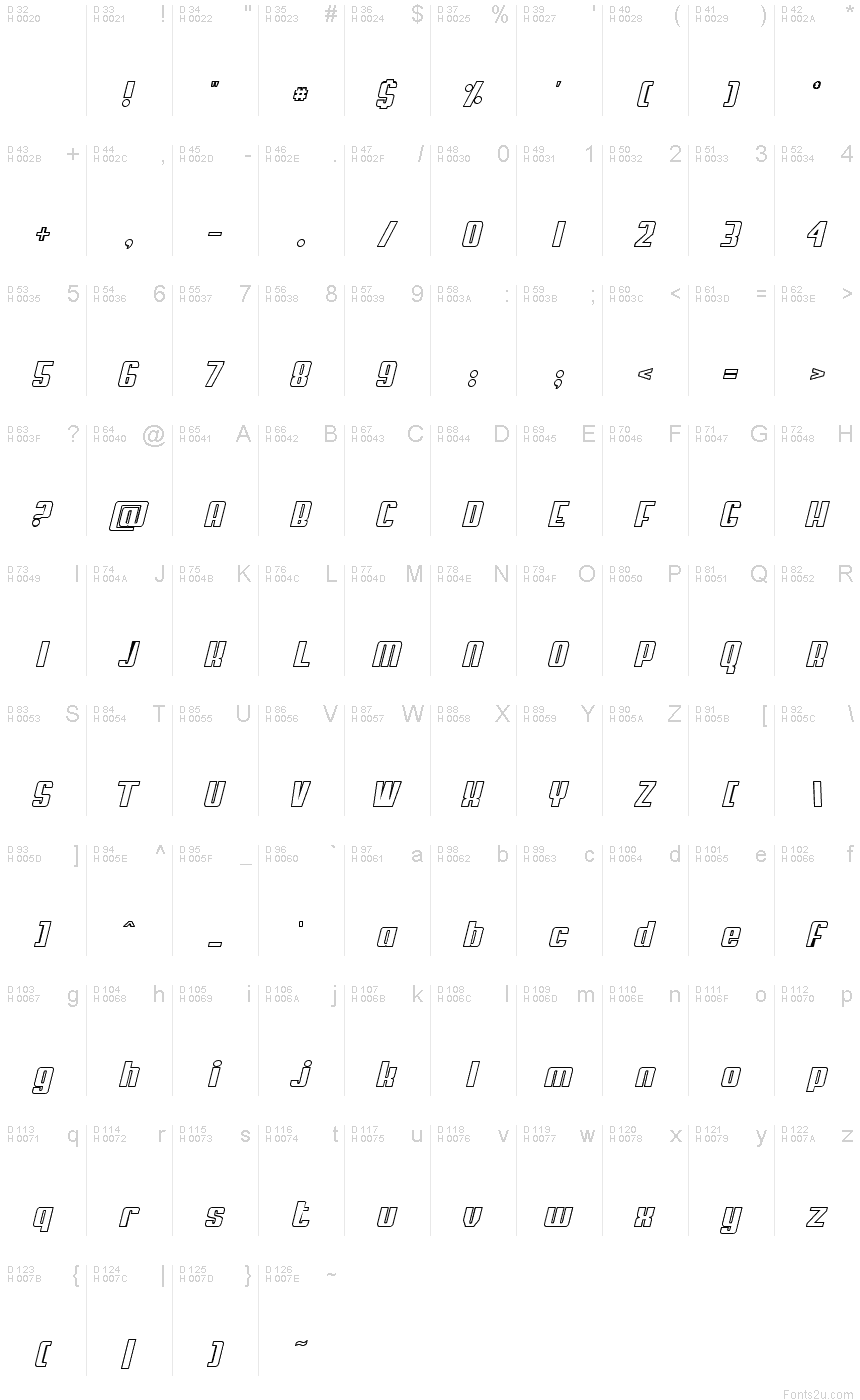
My Puma Oblique Outlined
My Puma Oblique Outlined von Samuel Park ist eine kostenlose Display-Schriftart mit schrägem, abgerundetem Design. Die Buchstaben bestehen aus einer durchgehenden Kontur mit offenen Innenräumen, was ihr einen hohlen, plakativen Look verleiht – perfekt für große Schriftgrößen.
My Puma Oblique Outlined eignet sich hervorragend für Logodesigns, Magazintitel, Sportgrafiken, Plakatlayouts und Albumcover, da die schrägen Formen und konturierten Striche ihre Wirkung auch bei großen Formaten beibehalten. Diese kostenlose Schrift ist zudem ideal für Branding-Akzente, Covertexte und kurze Werbeüberschriften, bei denen ein kompakter, grafischer Schriftstil die Botschaft allein transportieren soll.